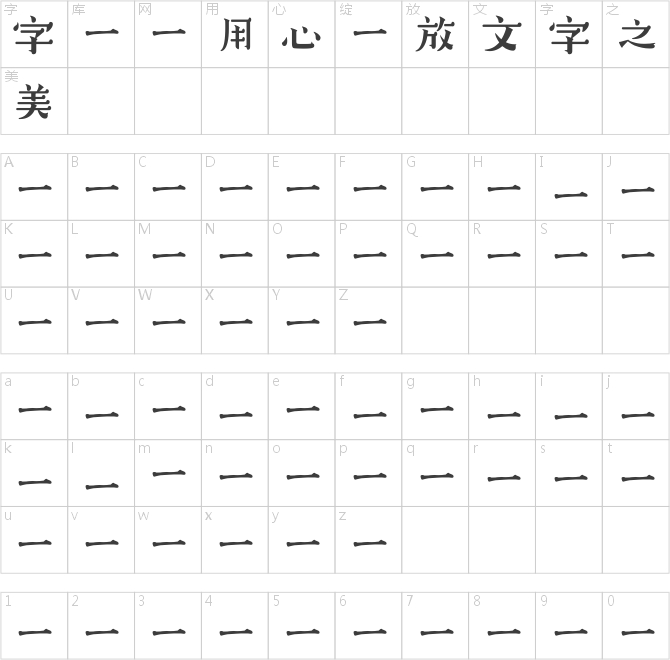
方正高原明朝體 詳情頁(yè)
明朝
方正高原明朝體是一款以作者母親名字命名的字體,字形基于宋體經(jīng)典且優(yōu)雅的結(jié)構(gòu)設(shè)計(jì)而成,減少了宋體具有相對(duì)鋒芒修飾感的字腳,筆畫(huà)圓潤(rùn)工整,韻律節(jié)奏恰如其分,構(gòu)建出一款字形修?、勻稱、雅韻,極具干練?華之氣質(zhì)美感的家族字體。 此款字體適合時(shí)尚、醫(yī)美、化妝品類行業(yè)廣告用字及畫(huà)報(bào)雜志標(biāo)題。